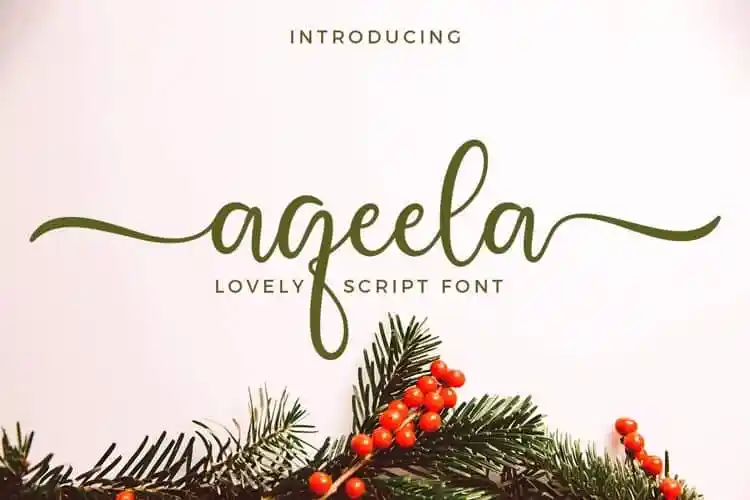
Aproveite a beleza única das letras à mão modernizadas com Aqeela Calligraphy Font. Esta elegante fonte moderna traz uma delicada adição de calligrafia, criando um impressiono impecável em cada letra. Perfeita para criar logotipos, estação móveis de casamento, cartas pessoais, designs personalizados como presentes e até mesmo as fotografias da sua vida. Além disso, oferece uma ampla gama de recursos que incluem vários set de estilo de letras e símbolos de várias línguas além dos números e sinais de pontuação. Com um total de 3 conjuntos estilizados – incluindo a ligação da silaba baixa com o coração (ss01), os saltos inicial e final da silaba baixa (ss02 e ss03) – Aqeela é uma escolha perfeita para seus projetos. Esta fonte abrange um conjunto completo de letras maiúsculas e minúsculas, além de símbolos multilíngues que permitem a você criar designs adaptados a qualquer idioma. Seja para cartões de aniversário, embalagens de produto ou até mesmo as frases escritas à mão que deixam seu estilo, Aqeela está aqui para tornar seus projetos ainda mais únicos e profissionais.